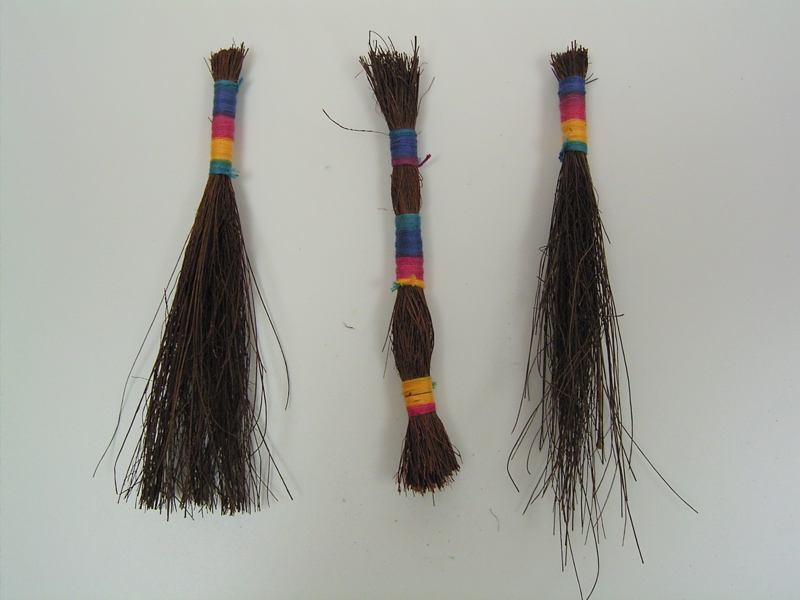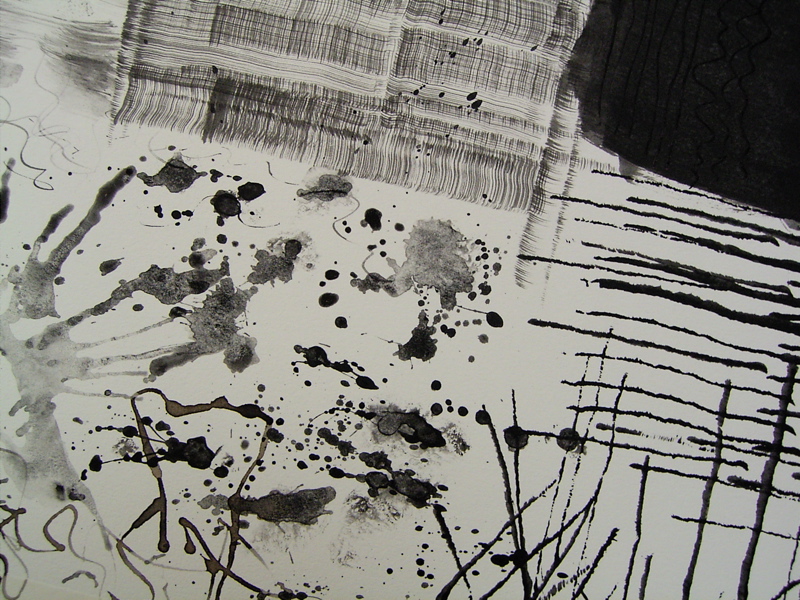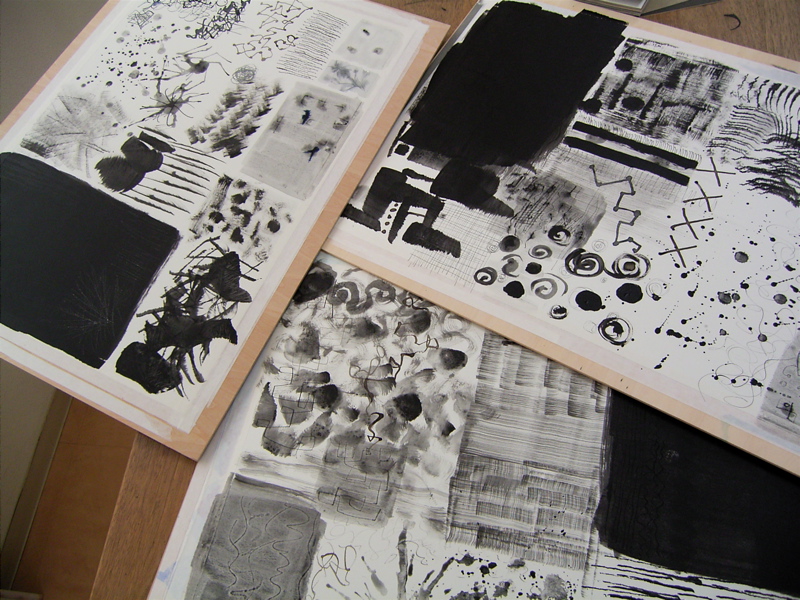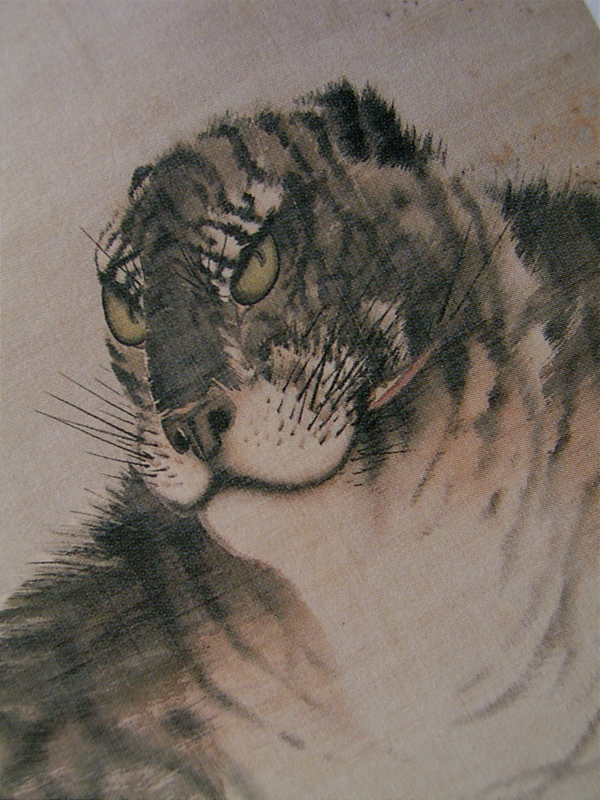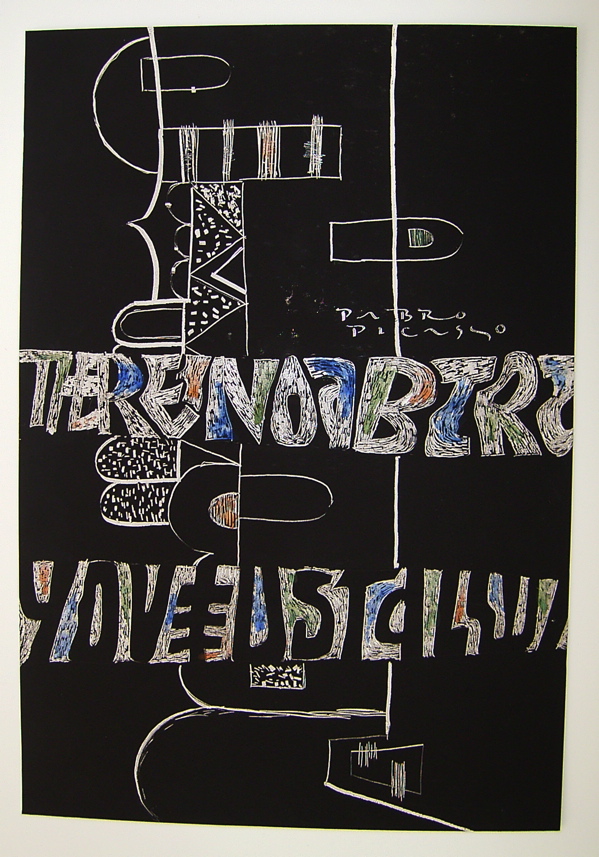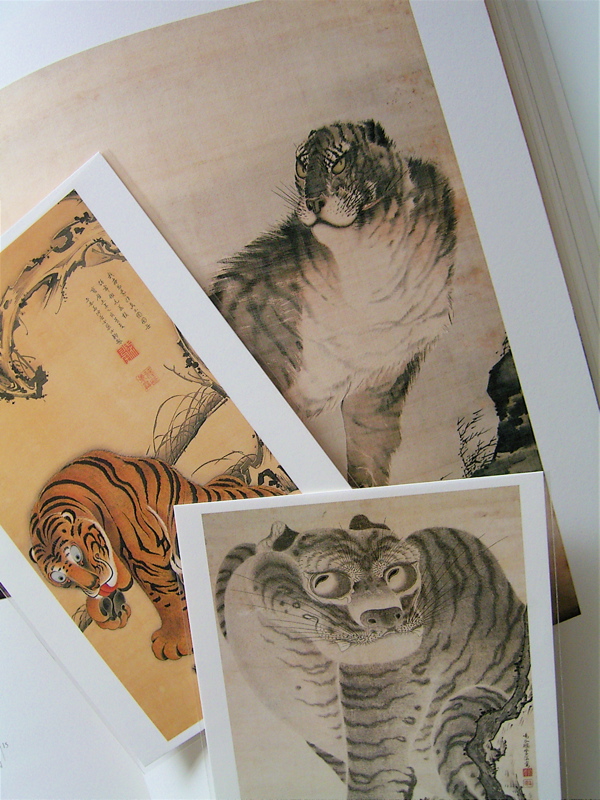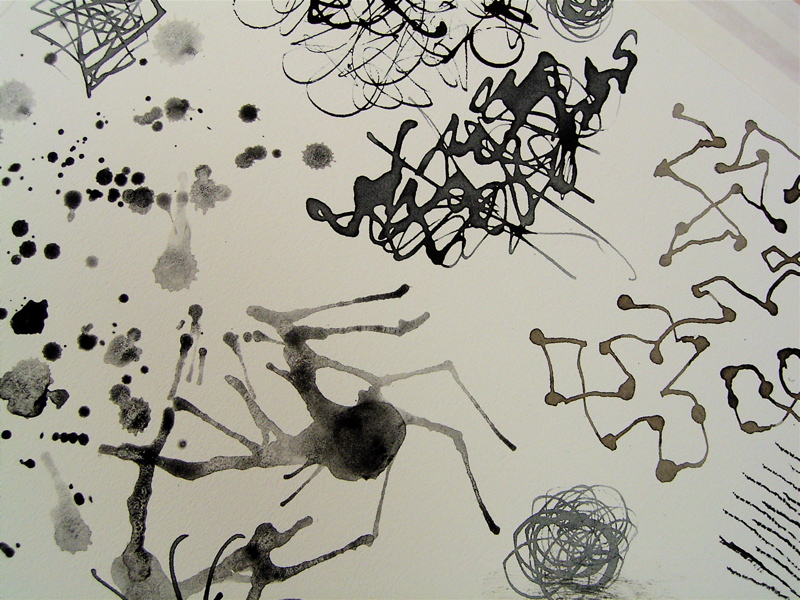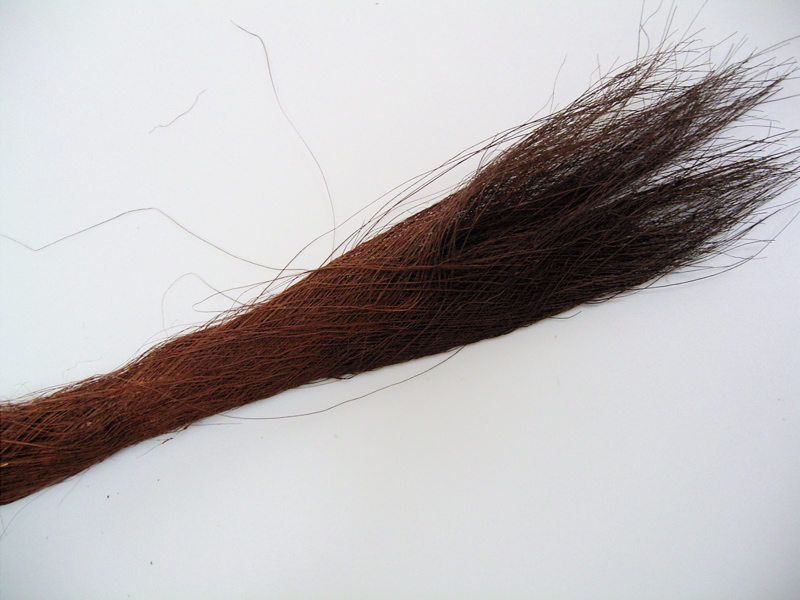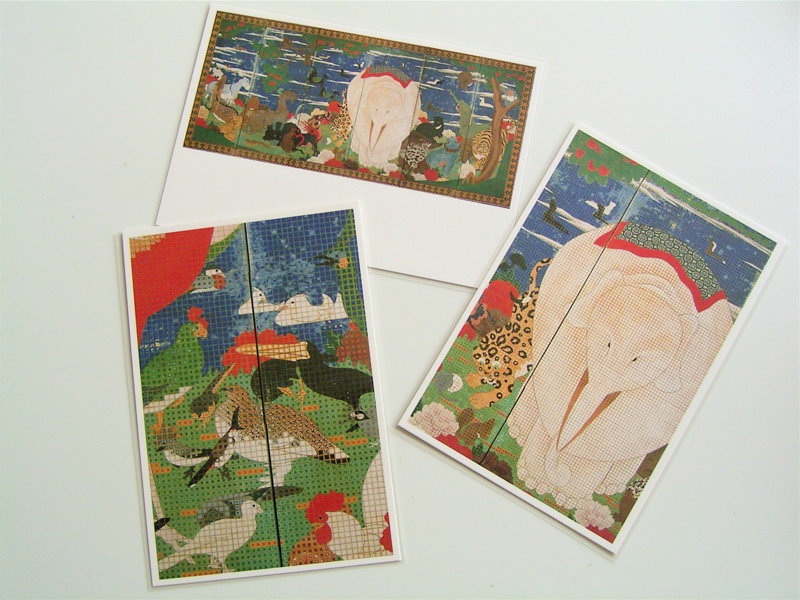
ベンシャーンのベースボール
毎年行っていますが、今回はとってもラッキーでした。
というのも、私がず〜〜と探していたベンシャーンの作品展の図録を発見しゲットできたからです。しかも、通常の2割引で。この図録には少々汚れがあるのですが、満足です。
1970年東京近代美術館で開催された作品展の図録です。なぜこれが欲しかったかというと、作品がたくさん載っていることもありますが、彼の描いたベースボールの絵をまた見たかったからです。
以前、これを持っている方から借りて見た時から、じつは虜になったページがありました。それをもう一度見たいと思っていました。
動きと線、何度見てもいいでしょう?!!
息子が少年野球をやっていた事もあり、親の会から出すお手紙やお知らせなどにこの絵を実はこっそり(ベンさんごめんなさい)使わせてもらっていたのです。
このまなざしは、レフト方向へヒットを打ってますね。表情も得意気です。
この腕のぎじょじょの線は一体どうやって描いたのでしょうね。
と言う訳で、今回の古本市は、なかなか良い収穫。三省堂の裏でやっている文具の販売所では、2000円ちかくする烏口を100円でもゲットできたし。
また来年もかならず行こう!古本市!
黒の楽しみ
以前もご紹介したのですが、月に2回のドローイングはいつも楽しい事をさせてもらえる実に楽しいクラスなのです、(先生ありがとう!)
そして今回はコラージュに挑戦です。まずコラージュに使う紙を作ります。色付きもたくさん作ったのですが、今日は黒だけの方をご紹介。
黒のアクリル絵具だけで模様を付けました。ベタも作ったりいろいろなテクスチャーを実験です。
参加者それぞれが一生懸命集中してやりますが、時々我に返ってフト隣を見ると、アラ!他の人のやっている事が気になる気になる! そうなのです、こういう作業は一人ではつまらない。何人かでやると楽しいのです〜〜 どうやったの?わたしもやろうっと言う感じ。
(mojitor-hさんの作った中にクモ発見)
次回この紙は切り刻まれて、おもしろいコラージュへと変身の予定。(あくまでも・・・予定・・・)
どんなことになっていくのか、また次回のお楽しみです。
イメージとしてはミロのような感じにしたい!でも無理かー!
それにしても、黒だけでこんなに楽しいなんてね〜。ずーっとやっていたいくらいでした。
もちろん最終的には文字を入れていきます。カリグラフィー作品として完成するかどうか!
期待せずにお待ち下さい。
キャベツ線
「薄く切りたい」→「スキャンしたい」…スキャンしました。
「じっと見ていたい」→「白黒にもしてみようかな?」…白黒
バージョンにしてみました。
理科の実験みたいです。昔からキャベツの表情が好きです。
理由「わかりません…」そういえば玉葱も好きかも。
「キャベツを線にしてみたい」→「ドローイングかな?」
紙にいくつも、いくつも線を書いてみました。
「kritzeln」ようするになぐり書きに近い状況です。いや落書きそのものでしょうか…。
くしゃくしゃ感を書いて、書いて、書いていきます…。
一番楽しい時間です。
キャベツ線は所を変え、布の上にも舞い降りました。
プリントごっこのお世話になり、麻布の上でグリグリ、
クシャクシャ、ビロビロしています…。
あ〜、キャベツ線にはscissor sisiters 「I don't feel like dancin'」
の調子の感じが似合います。(個人的意見ですが)
次回は玉葱線です。あなたはどんな野菜線を書きますか?
「えっ?そんなバカなマネはしない?」→「ご明解かも…」
スクラッチボード
東京白山のスタジオでは月に2回、羽賀洋子先生をおよびしてドローイングのクラスがあります。羽賀洋子
毎回、いろいろなカリキュラムを考えて下さり、楽しくカリグラフィーを織り交ぜたクラスを展開してくださっています。(このクラスにはmojitor-sとhも参加しているのです)
以前ギャラルリータイセイで見たコルビジェの作品にスクラッチした物があったので、いつかそれをやりたいという要望に応え、前回はスクラッチボードを使ってのクラスとなりました。
黒ボードを先端がとがったスラッチ用のニードルのような道具で描くと表面が削れ、下地の白が見えてきます。一度ひっかいたら直す事は出来ませんので、緊張しますが、そこがまた面白いところでもあります。
今回はちょうど神戸からいらっしゃってたH子さんも飛び入り参加です。もしかして、ペン先で直接かけるのでは?ということで試してみると、劇的に素晴らしい線が書けるではないですか!! ミッチェルでは弾力がありすぎてうまく行きませんが、ブラウゼなら大丈夫です。
カッパープレート体を書くポインティッドペンは、細い美しい線がでました。筆圧によって先が割れると、二重線になり、ますますきれい。
線だけでも絵と合わせても、非常に面白い世界が生まれます。いろいろな事を試せそうな画材ですね〜。あまりに楽しかったので、あっという間に時間が過ぎました。
笑顔の素敵な優しい先生です。
カリグラフィーをデッサンの世界とどう結びつけるか
一生懸命プログラムを組んでくださっています。
手作りブラッシュ
ついに馬のしっぽが手に入りました。これで書く道具を作ります。
なーんてことはある訳ないっす!
これはシュロの木の皮です。昨年大阪にワークショップを受講しに行った時、フリーマーケットで手に入れたものを分けて頂きました。
さて、これを書く道具へと変身させましょう。でもどうやって??
神戸のH子さんも同じ様に手に入れたこのフサフサを、糸でぐるぐる巻きにして書く道具を作っているのを以前見たので、私もそれに習ってやってみました。糸はしっかり巻き付けられる様に刺し子用の糸です。オリンパスの刺し子糸、色番74のミックスです。
勇んでやってみたものの、なんだかインデアンのタイガーリリーのお下げ髪か、お侍さんのちょんまげのようになってしまいました・・・・(ーー;)
ひゃぁーコワイ・・・・
でも、糸をしっかりぐるぐると巻き付けただけですが、ちゃんと書ける道具となりました。先を切りそろえたもの、そのままのもの、短いものと3種類です。
この試し書きの画像からではよくわからないかもしれませんが、非常にこまかく細い、割と硬い線が出ました。周りにピシピシとインクが飛んでいます。
先を切りそろえた短い方は、ステンシル用のブラッシュのようで、マークも文字も両方いけます。
ちょんまげブラッシュとして、これから私の道具のひとつとして活躍してくれそうです。
このやり方でいろいろと筆が出来そうという事が判明したので、こうなったらウマのしっぽを手に入れるしかないか!?
いえいえそれはもっとコワイので、ちかくの畳屋さんに行って、いぐさの切れ端をもらってこようかな・・・
伊藤若冲
伊藤若冲の展覧会に行きました。プライスコレクション 「若冲と江戸絵画」展 です。
朝早くに行ったのでさほど混雑はしていませんでしたが、お昼に近づくと徐々にすごい人でした。(朝9時半から開いていますのでオープンと同時に行くのをおすすめします)
こんな絵を18世紀に書いたんだなーと感心。色といい、デザインといい、現代アーティストと言われてもまったくわからない程の作品です。
私が好きだったのはなんといっても「鶴図屏風」とトラの絵です。
「鶴図屏風」は全部で12枚のパネルになっていて、そのひとつひとつの線が素晴らしいのです。すっとした線もあれば、ギジョギジョもあり、ほんわかだったりキリっとしてたり。そんな線で鶴が12羽。ひとつひとつの構図も素晴らしい!!
お土産で屏風に出来るアコーディオン式のカードをゲットしました。
トラは、顔がおもしろい。もうかわいいったらないのです。実物の虎ではなく、昔のふすま絵とか屏風から書いたらしいですが、足の裏をなめたり、目線がおもしろかったり、とにかくずーっと見ていてもあきない楽しさ。
特に私が好きなのは、入り口入ってすぐのこのトラ。
この自慢げな顔は人間です。ひげの線も毛並みの線もすばらしいし、顔の表情がなんと言ってもいいですねー!
この展覧会は8月27日まで東京国立博物館・平成館にて開催されています。この夏おすすめの展覧会です。
ドローイングは楽し!
ここのところ、デッサンクラスで線を書き、描き…。線を発見したり、感じたり、とにかく線って面白いです。
最初の頃は、物体を見てデッサンをするという基礎的なことをやっていました。
デッサンの先生はとてもアイデアウーマンで…、カリの世界を紹介したら興味津々になってくれました。いつか、カリの文字と組み合わせるようなカリキュラムへと発展させてくれたわけです。
こうなると下書きはありません。とにかく何か描きたいもの、実物でも写真でも構いません、線も様々な質で描き分けていきます。一本の線で美しく書いていくものや、短い線でつないでいくものや…ツールもカリペンを使ったりします。
ドローイングの線の質と合ったラインでカリ文字ものせていきます。このときもインスピレーション優先です。下書きはほとんどありません。一発で思うままに書いていきます。
この作業はスリリング!まぁ、でも失敗したらそれも楽しい〜。
クラスの皆さんの作品を見るのも楽しいしすごく勉強になります。みんな全然違う線を描くし、アイデアが面白いです。
イメージの線
現在来日中のカリグラファー、Brody Neuenschwandarの2日間のワークショップ「LINE」を受けてきました。笑点の様に「お題」が出され、それに合った雰囲気の文字を書いたのですが、これが楽しかった!これら3つはどんなイメージに見えますか?
ワラ筆と歯ブラシ
以前、ワークショップの参加者が持って来られた道具の中で、変わったツールを発見!
わら筆と歯間ブラシです。
ワラ筆の方は中国製で、のりで固められている穂先を水で濡らし、ほぐして使うのだそうです。ワラをまとめてしばってあるだけの物なのですが、非常に面白いラインが書けます。一見ほうきのミニチュア版みたい。
絵の具を沢山含ませることができないので、かすれた線が出来ます。太い線を出そうと思って絵の具を多く含ませると一度に紙に落ちてしまうのですが、それが細い線と水たまりでなかなかのコントラストです。
自分で作ろうと思っても、都会ではワラを手に入れる事は難しいですよね。今ちょうど新米の季節だから田んぼがあるところでは身近な素材なんでしょうが・・・。
歯間ブラシも面白いです。以外と書きやすく、ちゃんとペンの様に持って書けました。普通の歯ブラシだと寝かせて使うしかないのですが、これはブラシが柄に対して直角についているから大丈夫なんですね!
ただ、道具自体がちっちゃいのでやや不安定。でもかえって良い線を生むかもネ!